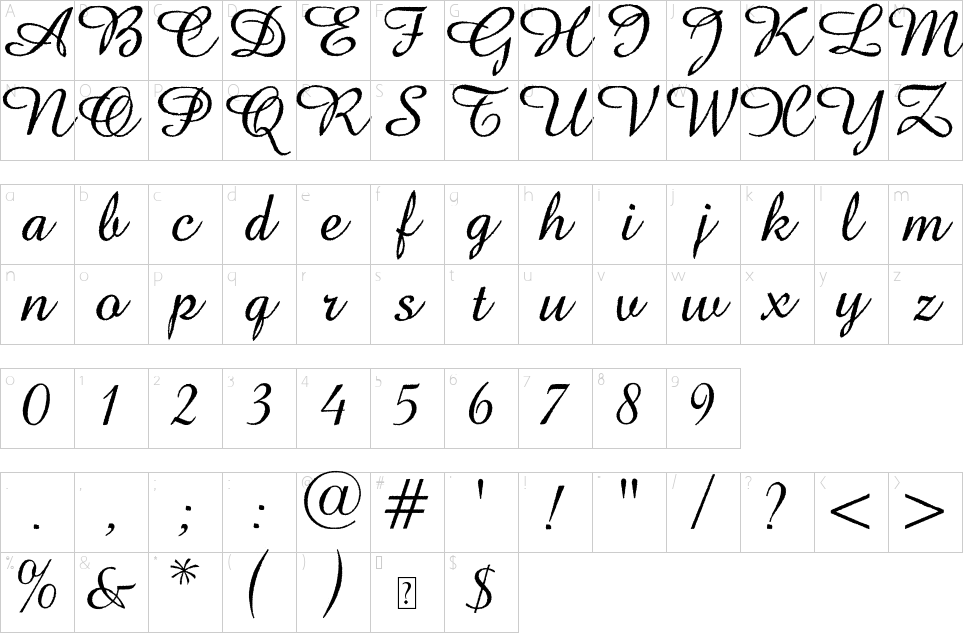
A Abbeyline Font é uma elegante e sofisticada escolha para os designers que buscam uma fonte elegante para projetos gráficos. Desenvolvida pelo designer Jose Alberto Reyes Galvez, esta fonte possui um design minimalista que se adapta perfeitamente a diversos tipos de projetos, desde editoriais até sites e aplicativos. Suas linhas precisas e equilibradas oferecem uma aparência moderna e sofisticada, tornando-a uma fonte de eleição para designers buscando uma solução minimalista e criativa. Com a Abbeyline Font, você pode adicionar um toque de sofisticação a qualquer projeto gráfico, sem comprometer a legibilidade. Disponível tanto para sistemas operacionais Windows quanto Mac, esta fonte é uma opção confiável e versátil para quem busca uma fonte de alta qualidade sem precisar pagar nada.